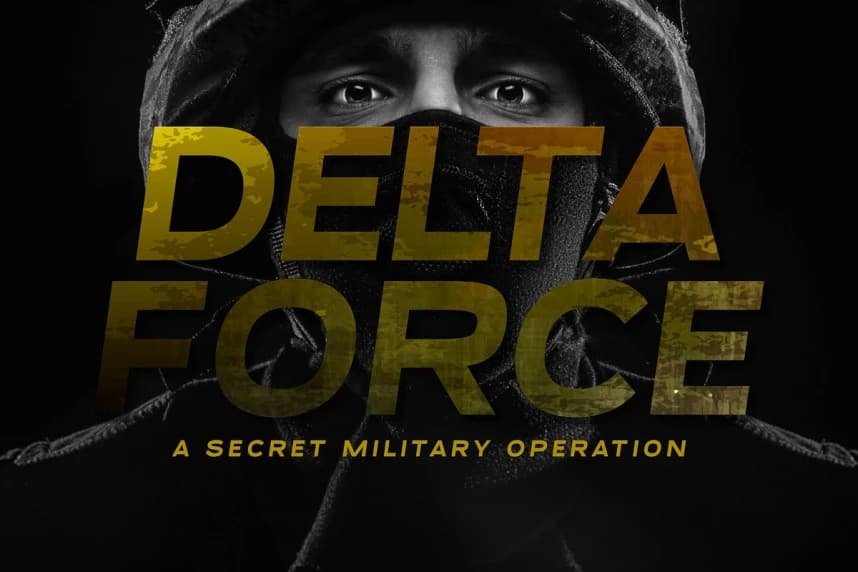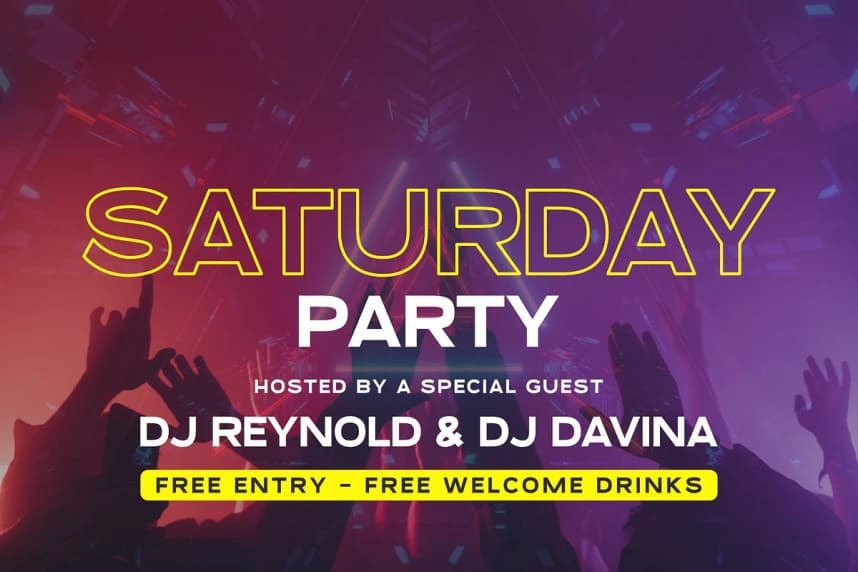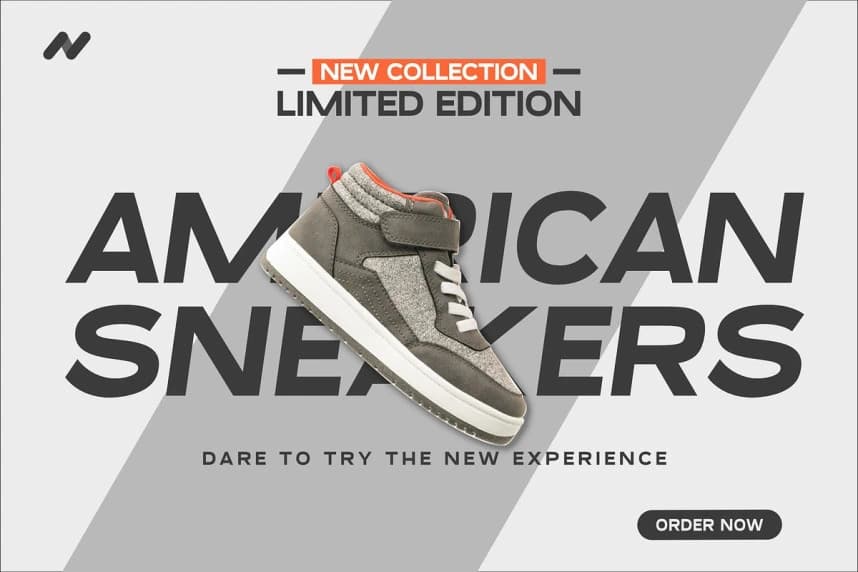
Balmont Yazı Tipi
Balmont Font, tasarım projenizin öne çıkmasını sağlayacak modern bir sans-serif yazı tipidir. Bu yazı tipi temiz ve geometrik şekiller, normal ve italik varyantlar ile sportif ve enerjik bir hava sunar. Logo, afişler ve el ilanları tasarlamanız gerekiyorsa
Balmont Font, tasarım projenizin öne çıkmasını sağlayacak modern bir sans serif yazı tipidir. Bu yazı tipi temiz ve geometrik şekiller, Regular ve Italic ile sporcu ve enerjik bir hava sunar. logolar, afişler ve broşürler oluşturmanız gerekiyorsa